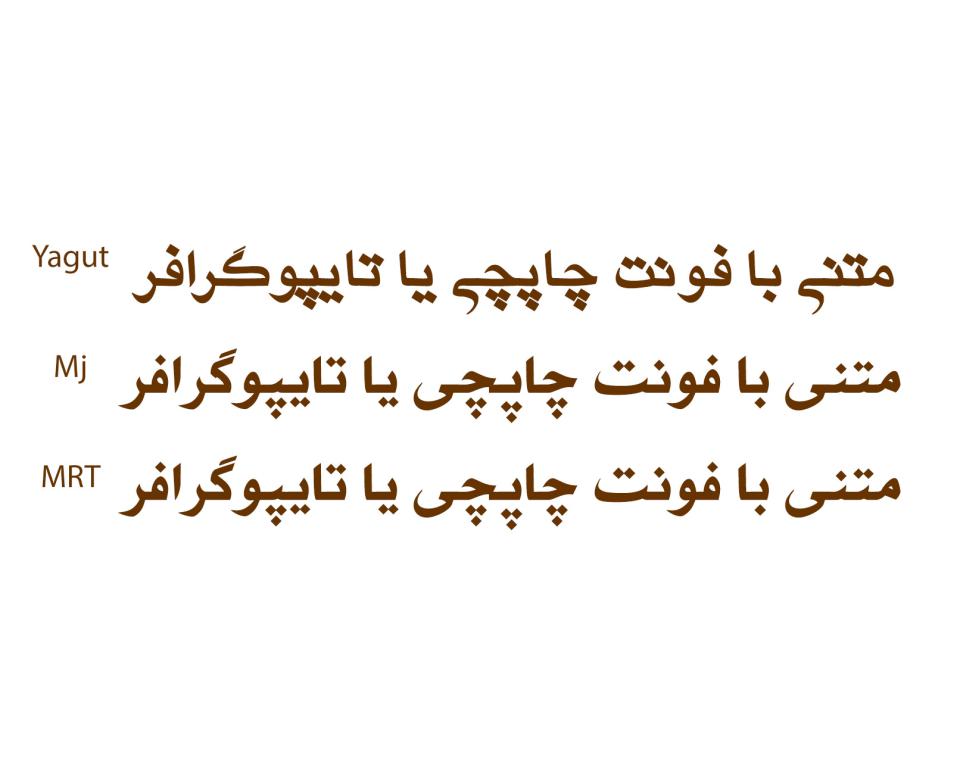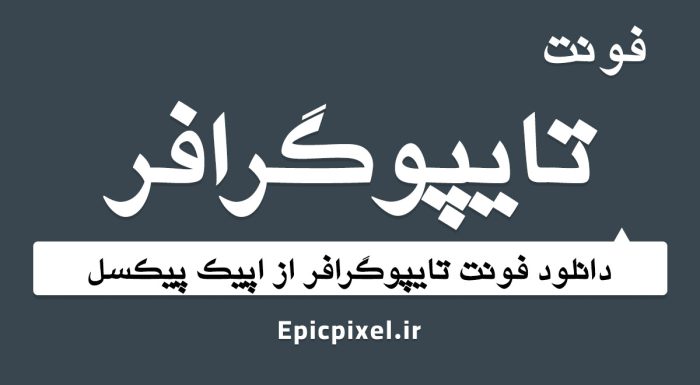
13 فونت تایپوگرافر فارسی
اگر به دنبال فونتی هستید که هم حس و حال سنتی داشته باشد و هم مدرن به نظر برسد، فونت تایپوگرافر فارسی یا همان چاپچی، انتخاب بسیار خوبی است. این فونت، با لبه های تیز و خاص خود، به نوشته ها جلوه ای ویژه می بخشد. فرض کنید می خواهید طرحی گرافیکی با حال و هوای قدیمی اما با ظاهری امروزی خلق کنید؛ فونت چاپچی دقیقا همان چیزی است که به آن نیاز دارید. این فونت رایگان است و به راحتی می توانید آن را دانلود کنید.
یکی از ویژگی های برجسته این فونت، وزن «یاقوت» آن است. این وزن، که به طور خاص برای تایپوگرافی مدرن طراحی شده، دارای پیچش های ظریف در انتهای حروف و نقاط لوزی شکل است. این ویژگی ها باعث می شوند که متن شما نه تنها خوانا باشد، بلکه بسیار چشم نواز و جذاب هم به نظر برسد. این ترکیب منحصربه فرد، فونت چاپچی را برای استفاده در طراحی لوگو، پوستر، جلد کتاب و سایر پروژه های گرافیکی که نیاز به یک فونت خاص و متفاوت دارند، ایده آل می سازد. در واقع، این فونت پلی بین سنت و مدرنیته ایجاد می کند و به طرح های شما هویتی خاص می بخشد.
شاید بتوان گفت که لبه های تیز این فونت در اندازه های بسیار کوچک، کمی خوانایی را کاهش دهد که البته در اکثر کاربردها مشکلی ایجاد نمی کند. با این حال، همین ویژگی، یعنی لبه های تیز، در اندازه های بزرگتر، زیبایی و جذابیت خاصی به متن می بخشند. به طور خلاصه، اگر به دنبال فونتی رایگان، زیبا، با ویژگی های خاص و مناسب برای انواع پروژه های گرافیکی هستید، فونت تایپوگرافر فارسی (چاپچی) با وزن یاقوت خود، انتخابی هوشمندانه خواهد بود.